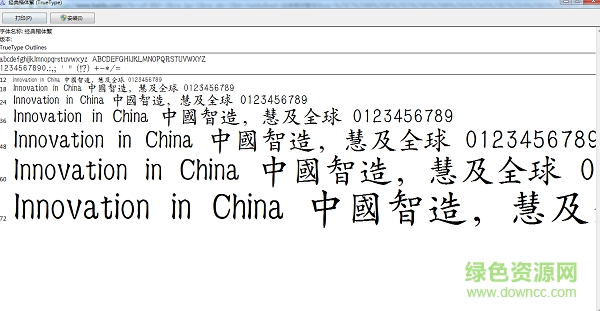
經(jīng)典楷體繁體
經(jīng)典楷體繁字體是一款設(shè)計非常漂亮的中文繁體字體,字體骨絡(luò)分明,線條有粗有細過渡自然,結(jié)構(gòu)端正規(guī)范,可應(yīng)用的范圍非常廣泛,需要更多楷體的朋友歡迎在綠色資源網(wǎng)下載!
楷書特點介紹
楷書也叫正楷、真書、正書。楷書的特點在于規(guī)矩整齊,是字體中的楷模,所以稱為楷書,一直沿用至今。
經(jīng)典楷體繁
楷書發(fā)展歷程
楷書的萌芽期——秦漢,
楷書發(fā)展期——魏、晉、南北朝,
楷書繁榮期——隋、唐、五代,
楷書守成期——宋、元、明、清。